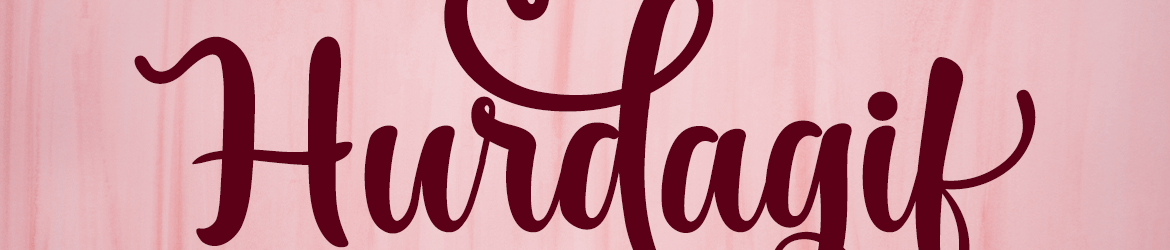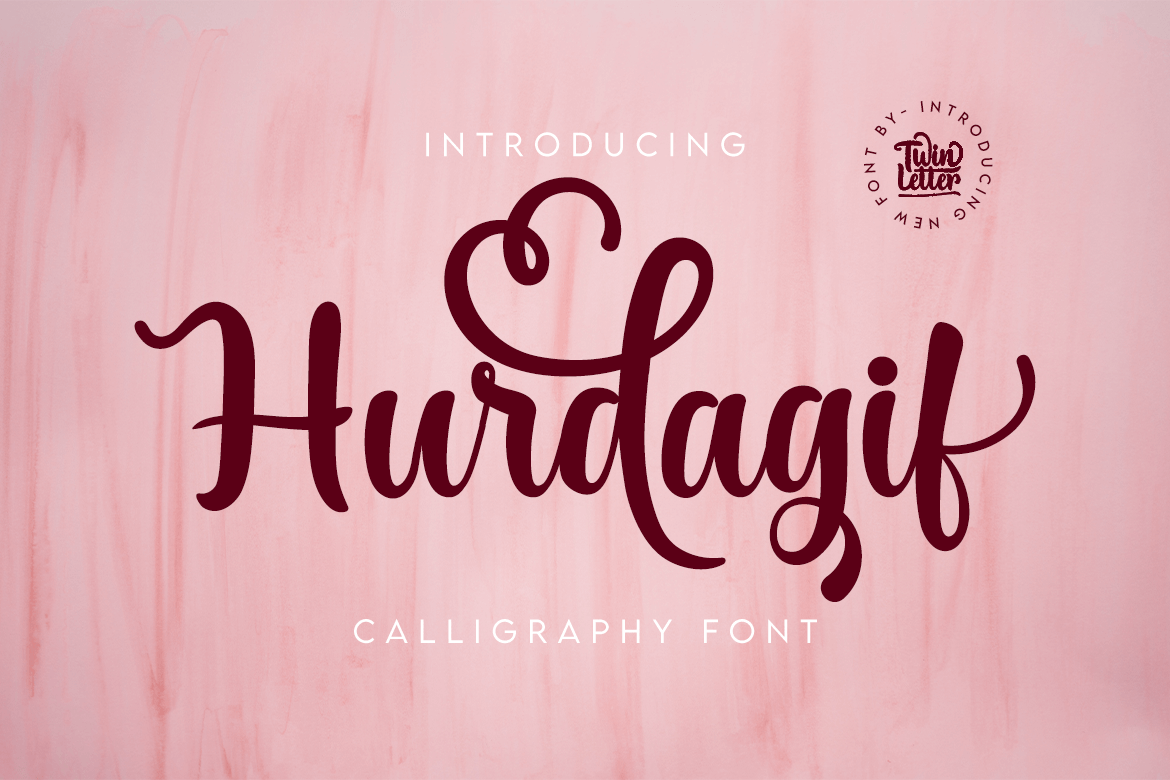
Hurdagif Font – Fonte Grátis
Hurdagif Font
Esta é uma fonte de caligrafia com traços românticos e suaves que parece dançar ao longo do nível base. É perfeita para adicionar um toque sofisticado a qualquer projeto de design que você possa criar! Esta fonte está PUA codificada, o que significa que você pode acessar todas as incríveis letras e ligaturas com facilidade. Seja para gráficos digitais ou impressos, Hurdagif é uma escolha ótima que adicionará um toque elegante a qualquer projeto.